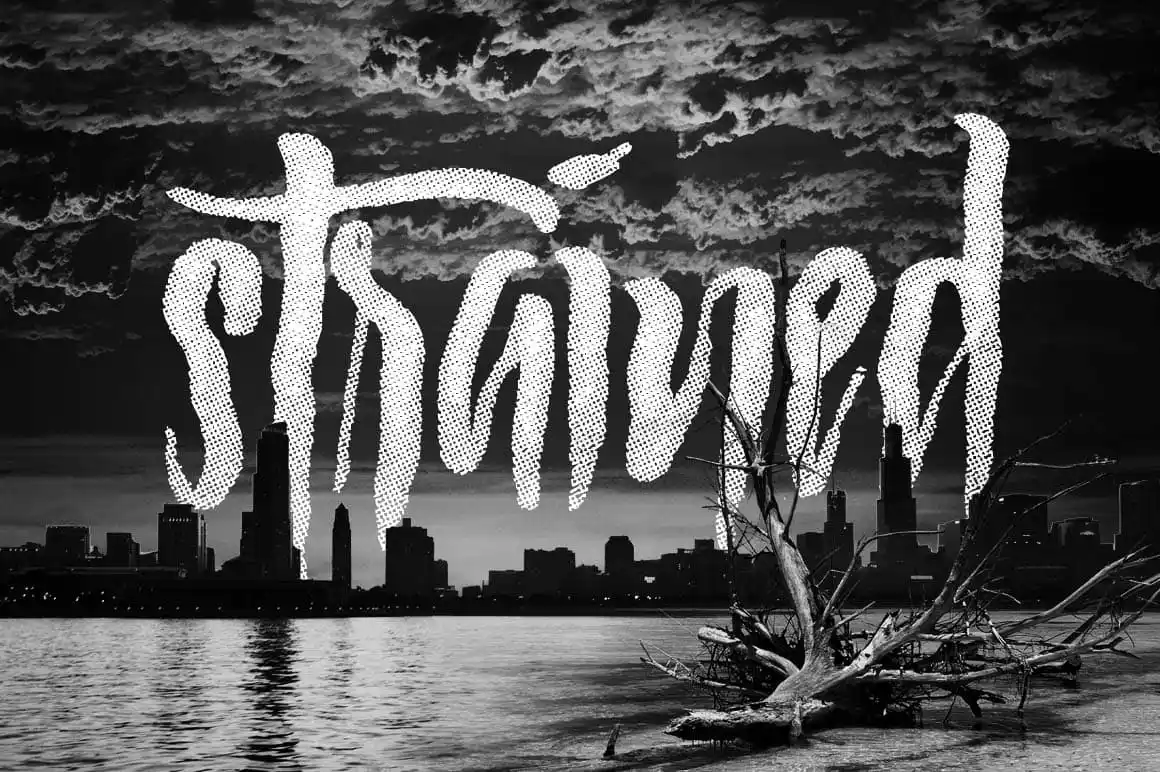
Strained Brush Font – Download Grátis
Esta fonte ‘Strained Brush Font’ é uma versão refinada do estilo desenhado à mão que você encontrará na coleção The Branded Quotes. Ela é perfeitamente adaptada para criar um texto com efeito brush, adicionando um toque único e autêntico a qualquer design gráfico. A fonte foi criada pelo designer Hamilton, oferecendo uma experiência de leitura fluida que mistura elementos modernos com um ar vintage elegante. Descarregue esta fonte e experimente suas capacidades incríveis em seus projetos. Enjoy 😉